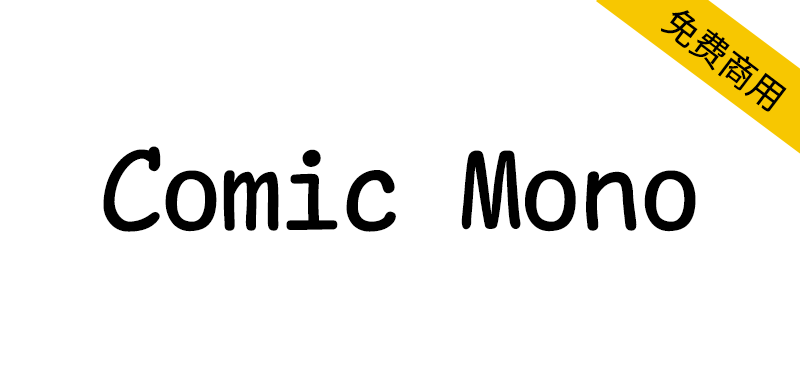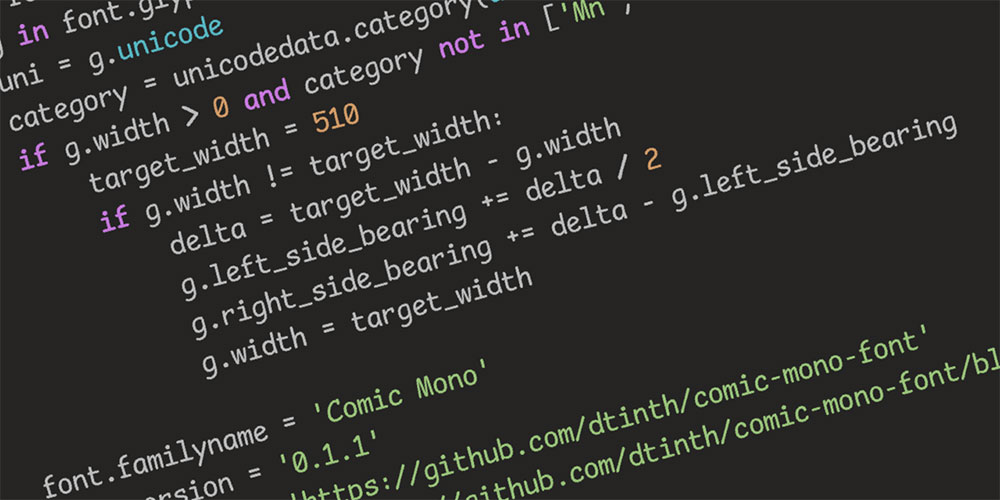
Comic Mono是一种清晰易读的等宽字体...正是你自幼便习惯识别的经典字型。源自Shannon Miwa创作的Comic Shanns。与 Comic Shanns 的差异如下:
等宽调整:所有字形均经过调整,确保严格等宽(基于 monospacifier 的代码实现)。
字距优化:参照 Cousine 字体的参数调整字形间距,使其与系统字体混排时显示更协调。
更名:字体名称改为 Comic Mono。
粗体版本:通过 FontForge 的“加粗”功能生成对应的粗体样式。
相关字体推荐与区别说明:
Comic Shanns:新增支持重音字符和数学符号等特殊字符
Comic Shanns Mono: 基于 Comic Shanns 开发,调整了字体度量并增加了更多字符。
Serious Shanns:进行了更多优化,进一步提升可读性,采用更纤细的字重,并提供 Nerd Font 版本。
A legible monospace font... the very typeface you’ve been trained to recognize since childhood. This font is a fork of Shannon Miwa’s Comic Shanns (version 1).Differences from Comic Shanns:
All glyphs have been adjusted to have exactly the same width (using code based on monospacifier).
The glyph metrics have been adjusted to make it display better alongside system font, based on Cousine’s metrics.
The name is changed to Comic Mono.
A bold version of the font is generated using FontForge’s Embolden operation.
Check out these fonts as well
The original Comic Shanns by Shannon Miwa has V2 released with support for accented characters and other symbols, such as math symbols.
Check out Serious Shanns by Kyle Beechly, which has more modifications to further enhance the legibility, lighter weight, and Nerd Font version.
Check out Comic Shanns Mono by Jesus Gonzalez, which is based on Comic Shanns v2 but with metrics adjusted and with more additional characters.